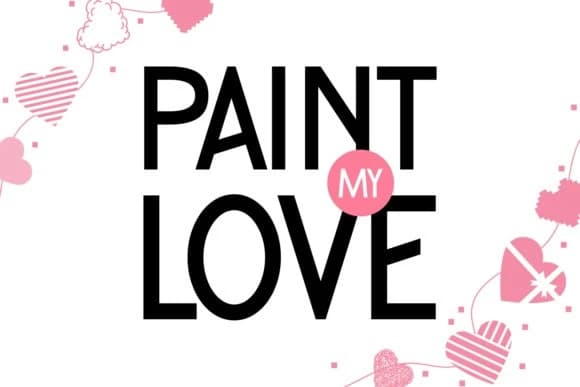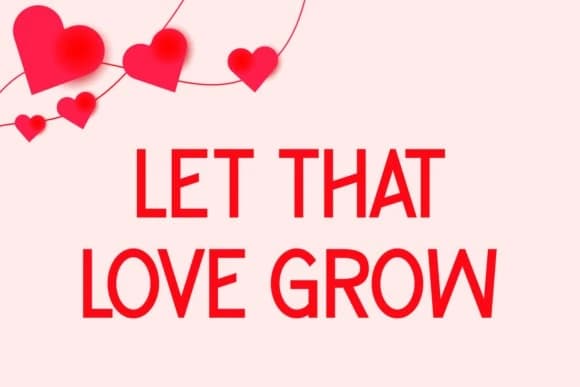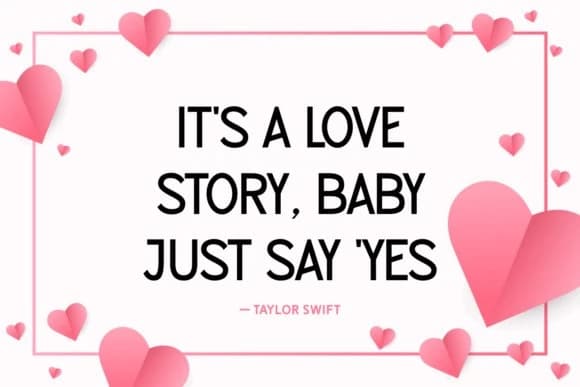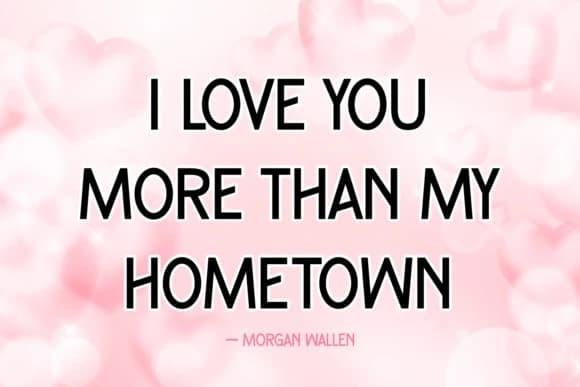
Paint My Love Font
Paint My Love Font, cesur ve kendinden emin bir sans serif fontudur. Konu ne olursa olsun, bu font, fontlarınızın kütüphanesine inanılmaz bir değer katacak ve herhangi bir yaratımı yükseltme potansiyeline sahiptir.
Paint My Love Font, cesur ve kendinden emin bir sans serif yazı tipidir. Konu ne olursa olsun, bu yazı tipi fontlarınızın kütüphanesine inanılmaz bir katkı sağlayacaktır; çünkü herhangi bir yaratımı yükseltme potansiyeline sahiptir.